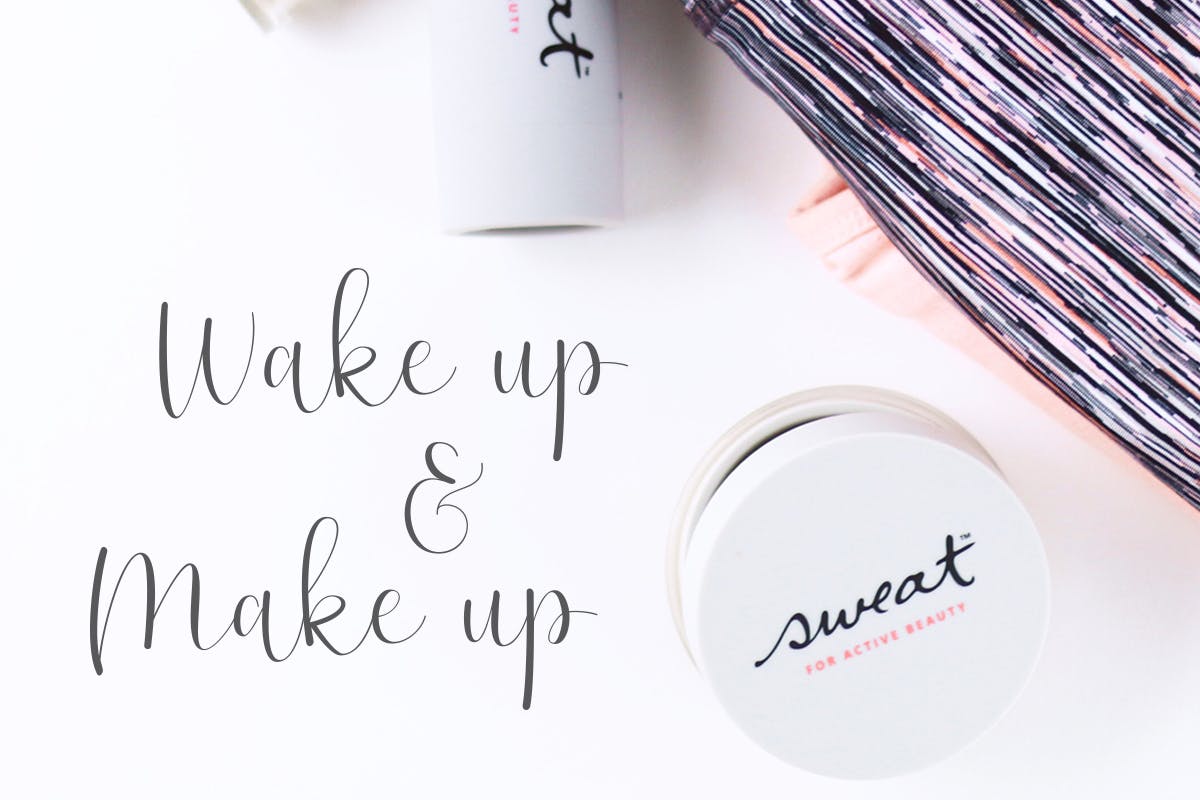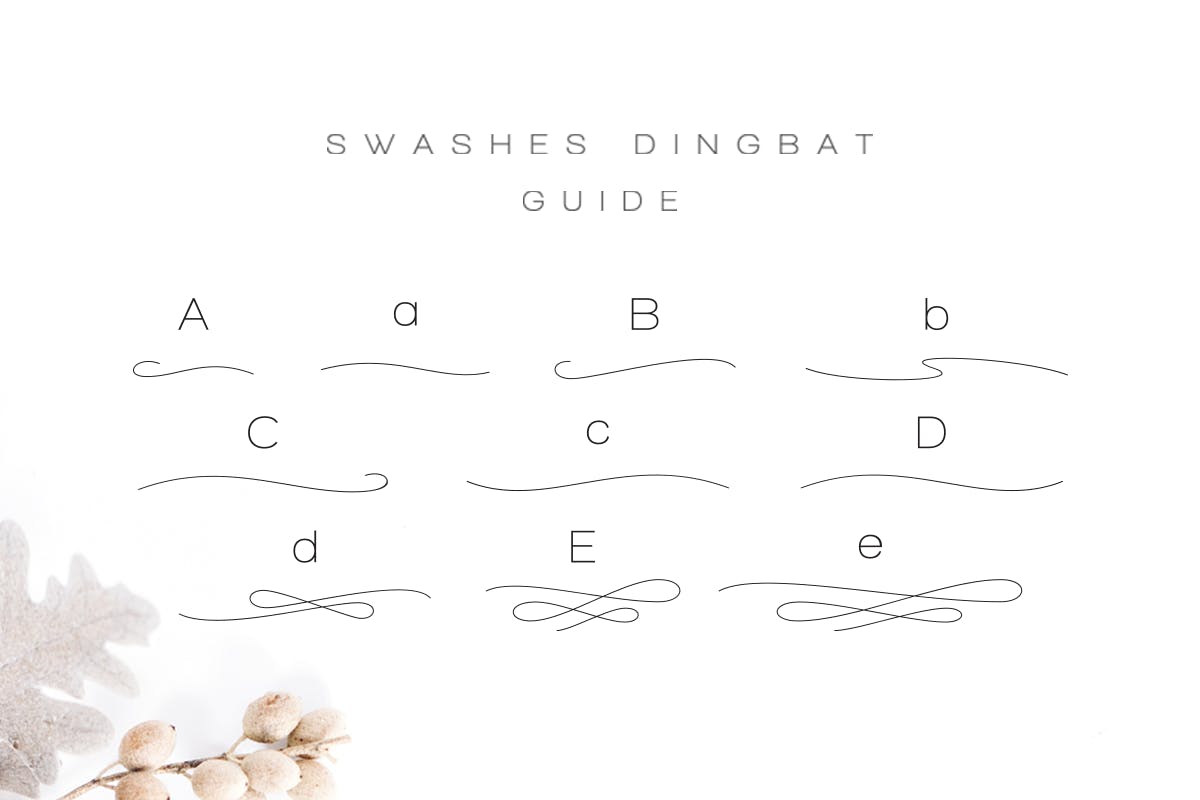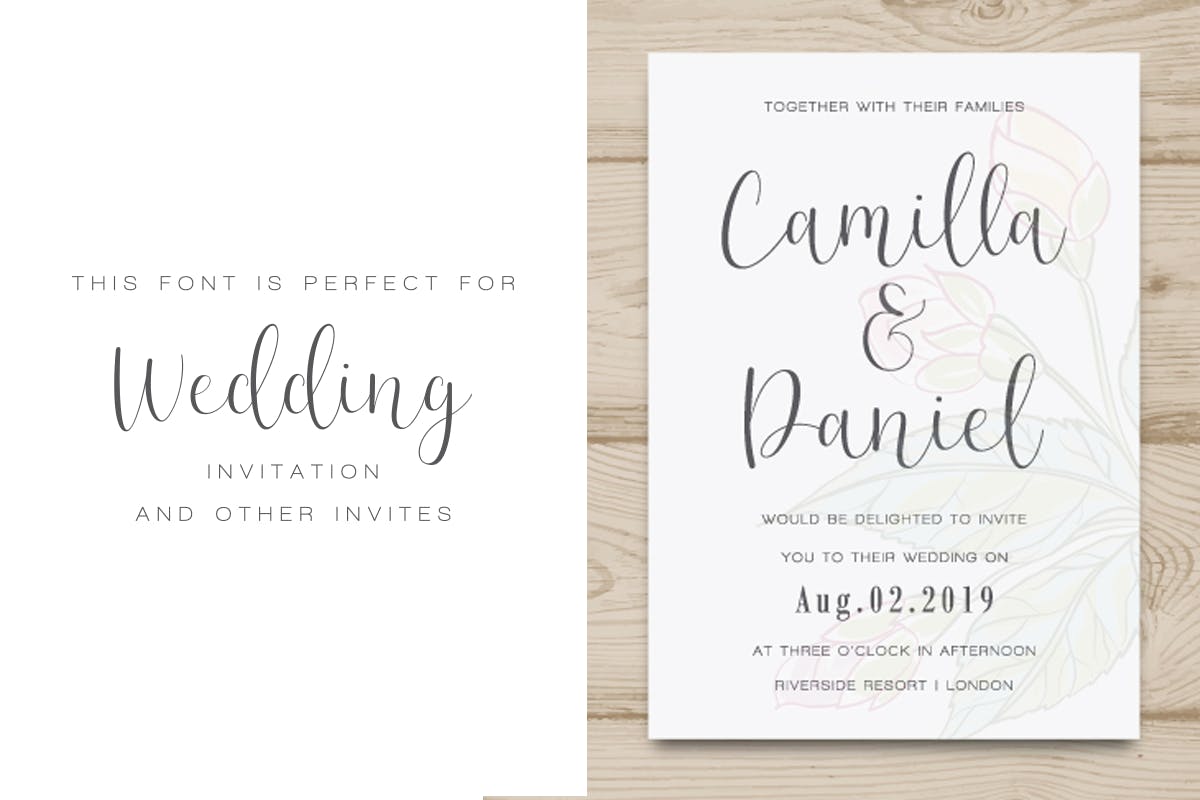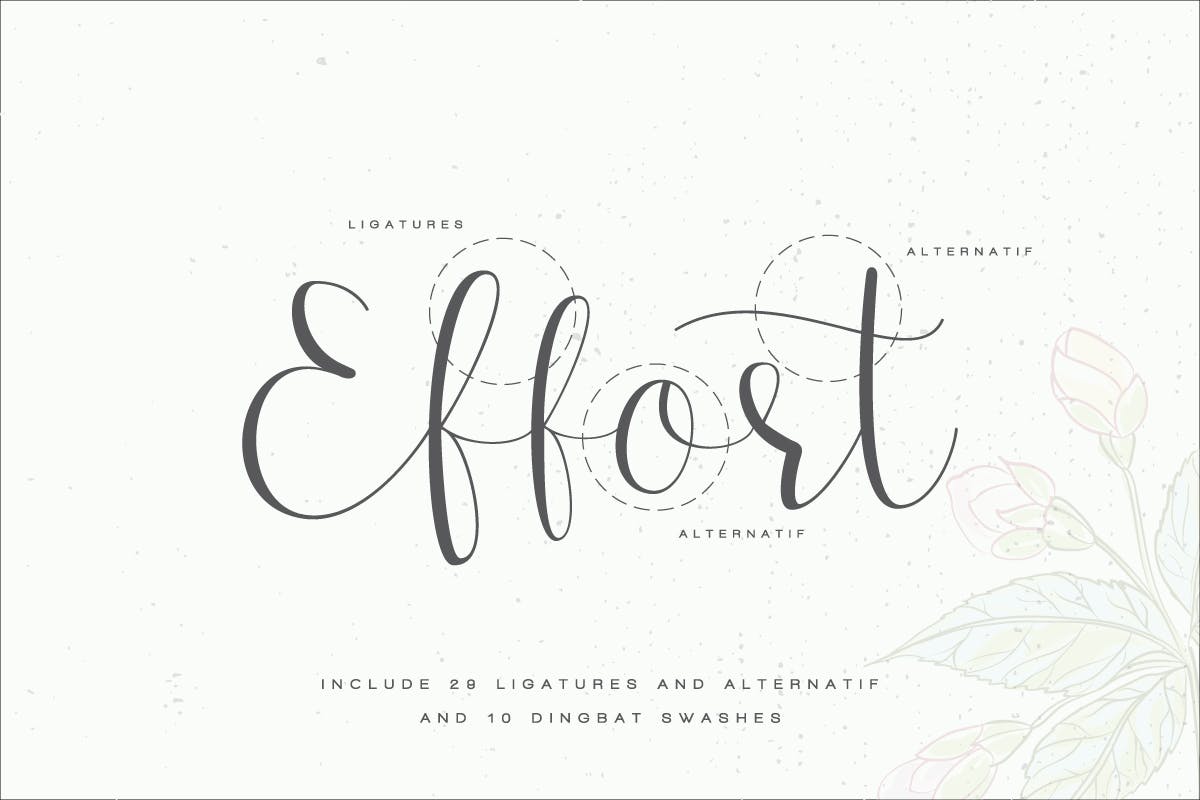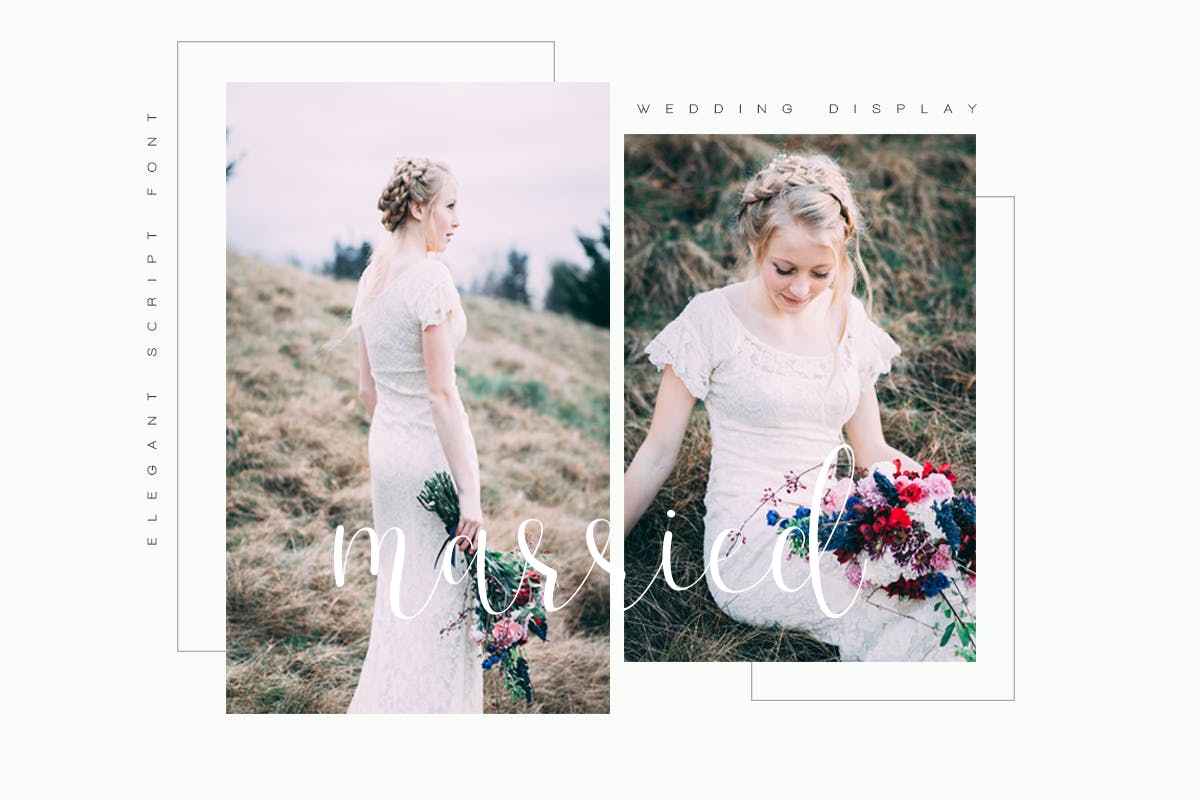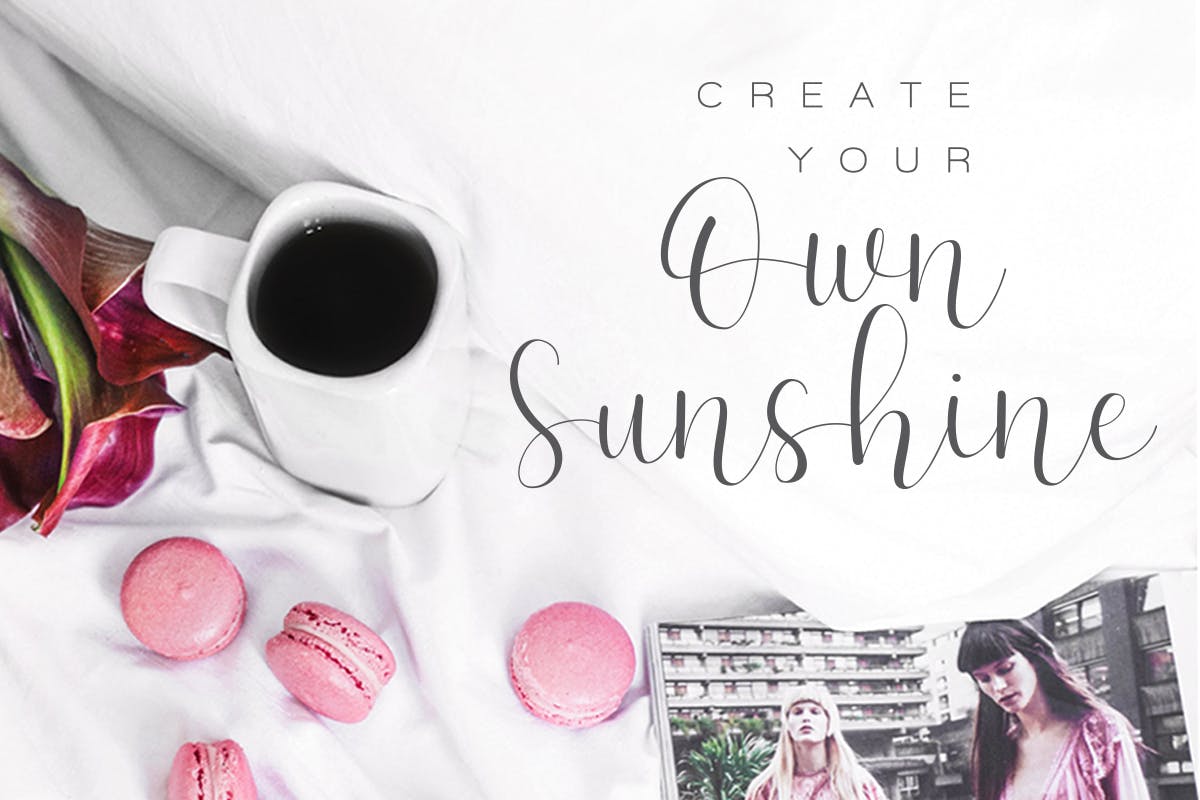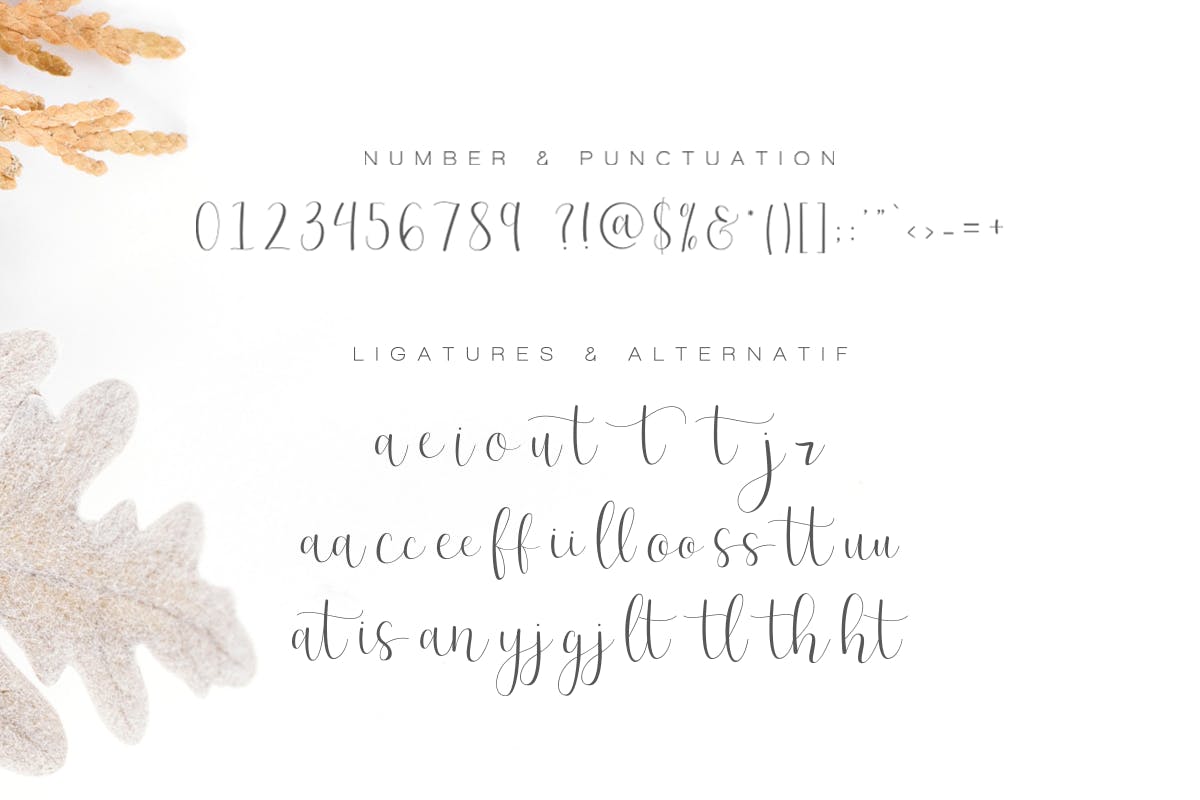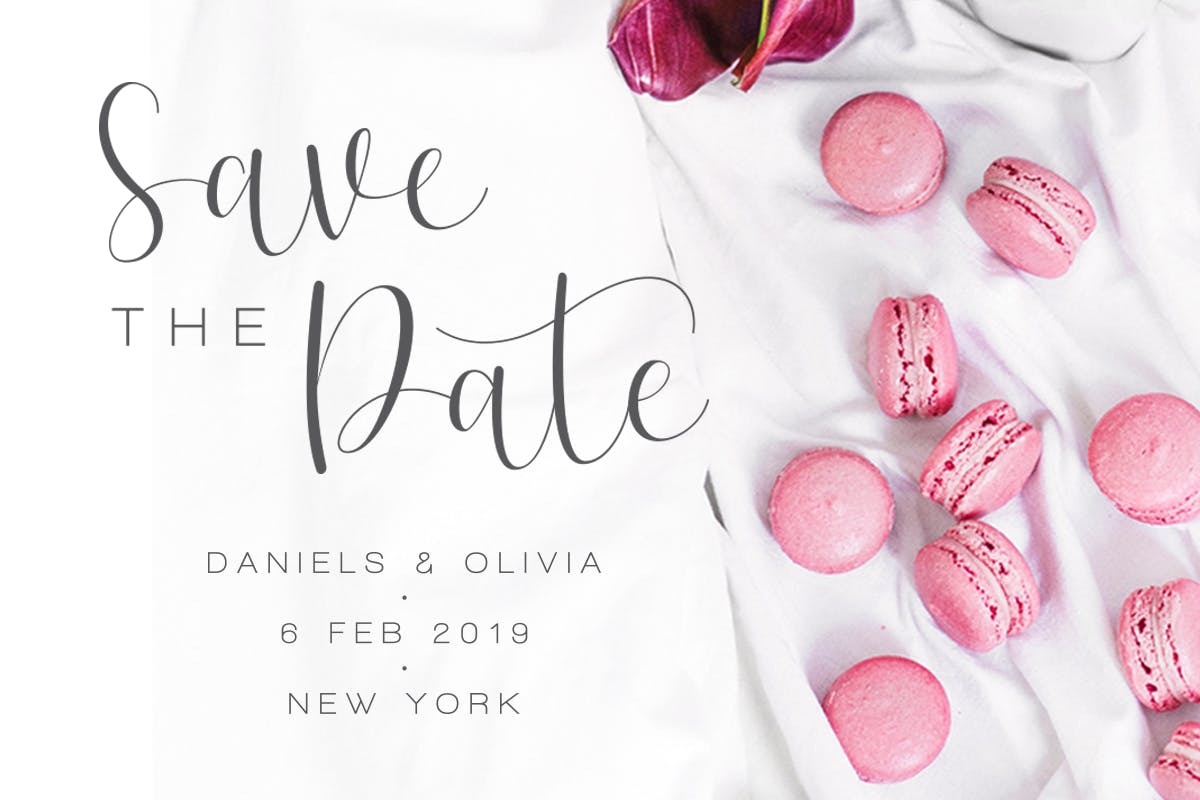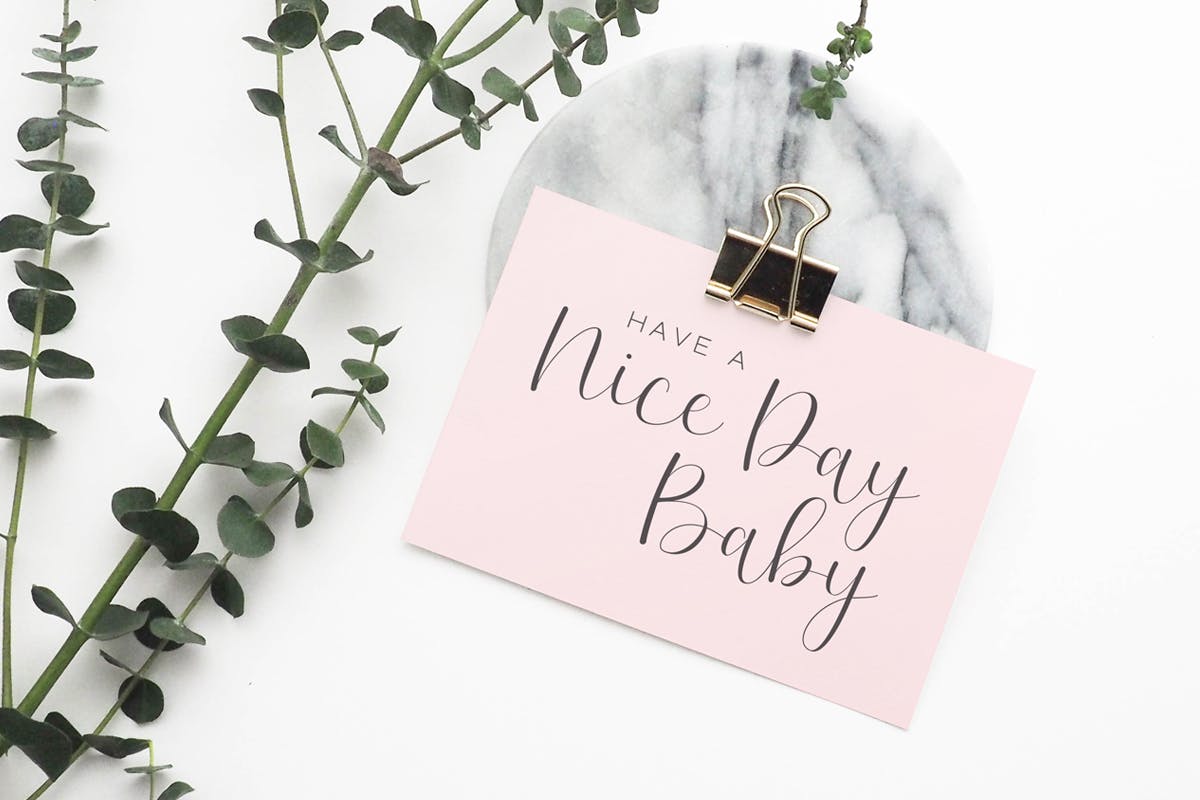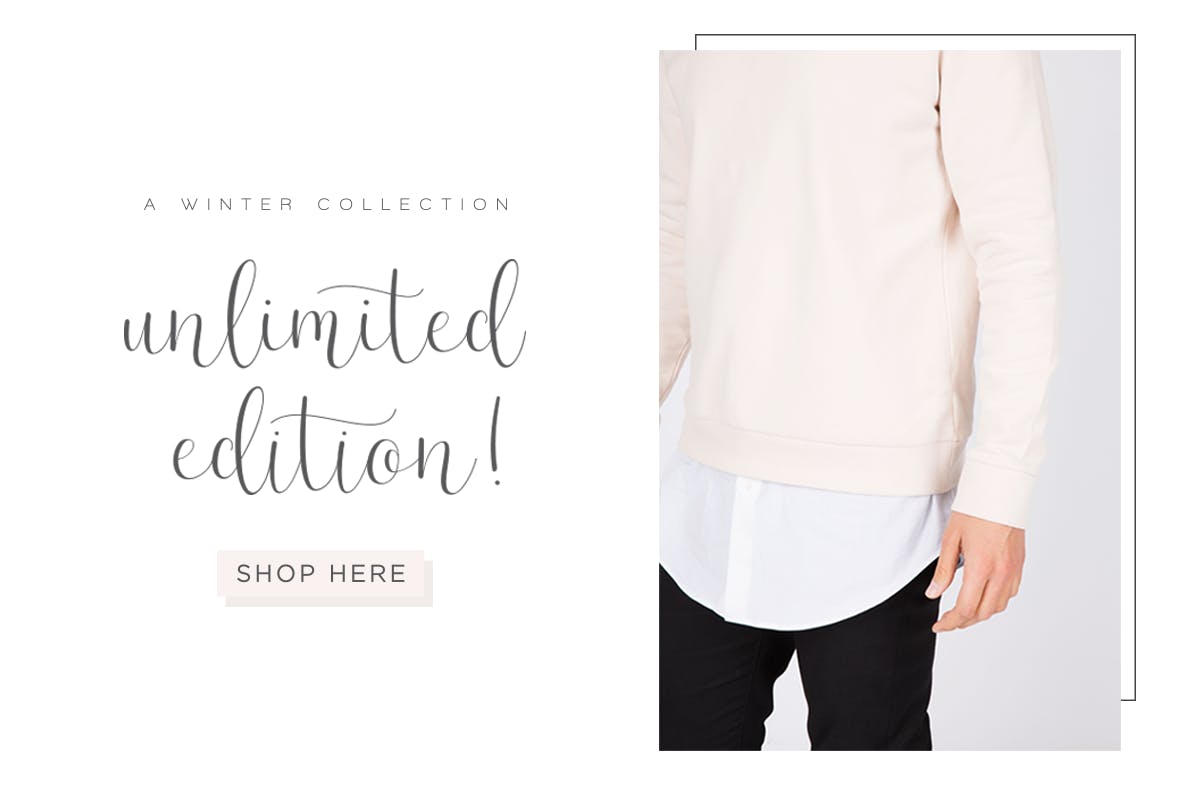
به شما فونت جدید و زیبای Effort Calligraphy معرفی میشود!
فونت Effort یک فونت کالیگرافی مدرن با طراحیهای دستنویس و پیچیده است. این فونت برای برندینگ، دعوتنامههای عروسی و کارتها بسیار مناسب است.
اگر به دنبال یک لمس از ظرافت و مدرنیته برای طراحیهای خود هستید، این فونت بهخصوص برای شما طراحی شده است :)
فونت Effort با ویژگیهای OpenType، جایگزینها، لیگاتورها، نشانهگذاری، اعداد و همچنین پشتیبانی از زبانهای دیگر ساخته شده است :)